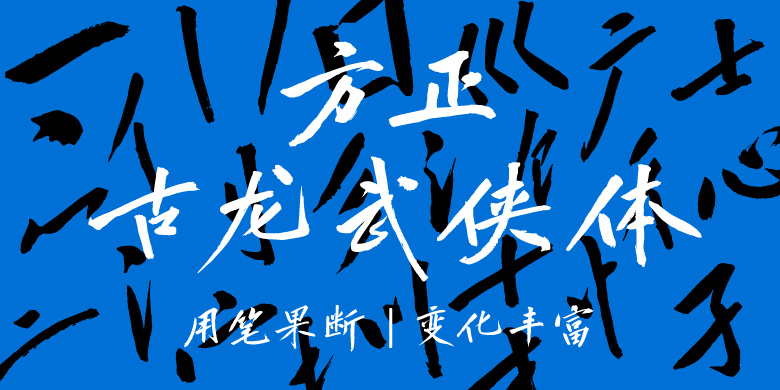
方正古龙武侠体
方正古龙武侠体,这款字体结构工整、笔画清晰,兼顾美观与易读性,适用于标题、正文、海报、包装、LOGO 等多种场景。字形优雅稳定,风格百搭耐看,适配日常排版与创意设计,让文字呈现更舒适、更具质感。方正古龙武侠体一笔一画,皆是细节,以均衡的比例、流畅的线条打造舒适视觉体验,字形端正大气,风格简约现代。无论是商业设计、品牌宣传还是日常排版,都能轻松驾驭,让文字更有格调与力量。方正古龙武侠体字体下载。
“方正古龙武侠体”是由方正字库和腾讯共同打造的一款汲取了古龙先生字体的笔触特点和结构体态的全新创写且适用于排版的手写字体。“武侠体”的设计,用笔果断,在书写设计过程中保持毛笔书写韵律,富于字体变化却不失和谐之美,融合了古龙先生武侠书风的气派,并考虑字库的易辨性和适用性,前期进行了多次方案设计及优化调整,最终成库的“武侠体”适用于影视剧、游戏、动漫、衍生品的海报标题字使用。
主创设计:周佳敏,设计指导:汪文